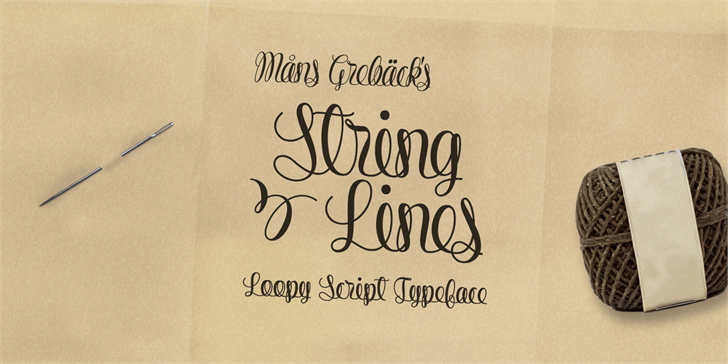
String Line Script Font
Introduzimos a String Line. Esta tipografia foi criada pelo designer Måns Grebäck e apoia múltiplas línguas. A String Line é um tipo de escrita fluída, com seus elegantes torções conectadas para formar formas de letras espirais. Este font é incrível para diversos projetos como: fotografia, marca d’água, citações, cabeçalho de blog, cartazes, casamento, marca, logotipo, moda e roupas, nome, convites, correspondência, entre outros. Como a descrição original nos revela, a String Line é uma fonte de script ideal para estilos criativos e personalizados. Se você está procurando por uma fonte de escrita fluída que possa se adaptar perfeitamente ao seu projeto específico, provavelmente vai apreciar a String Line do designer Hamilton.